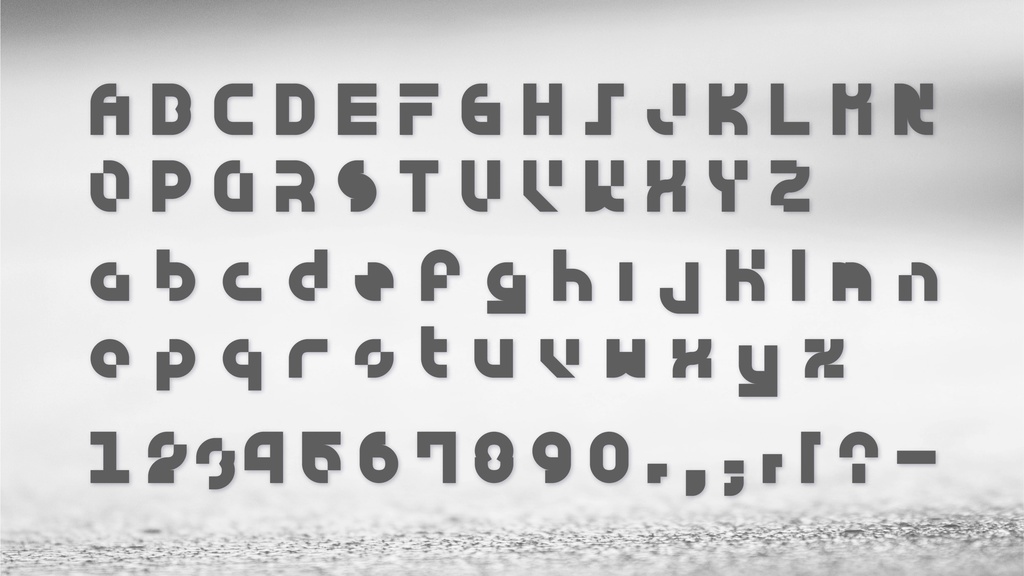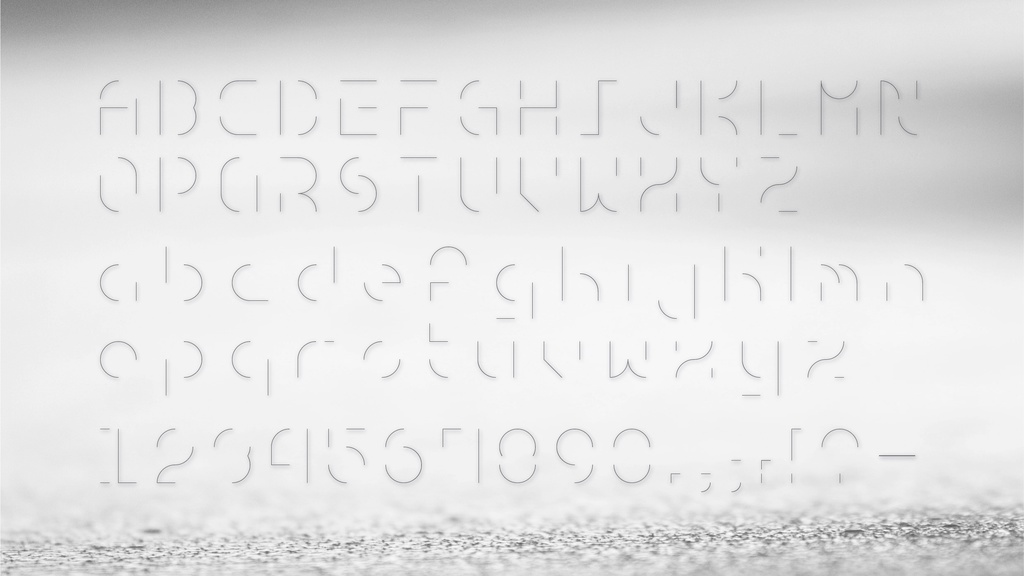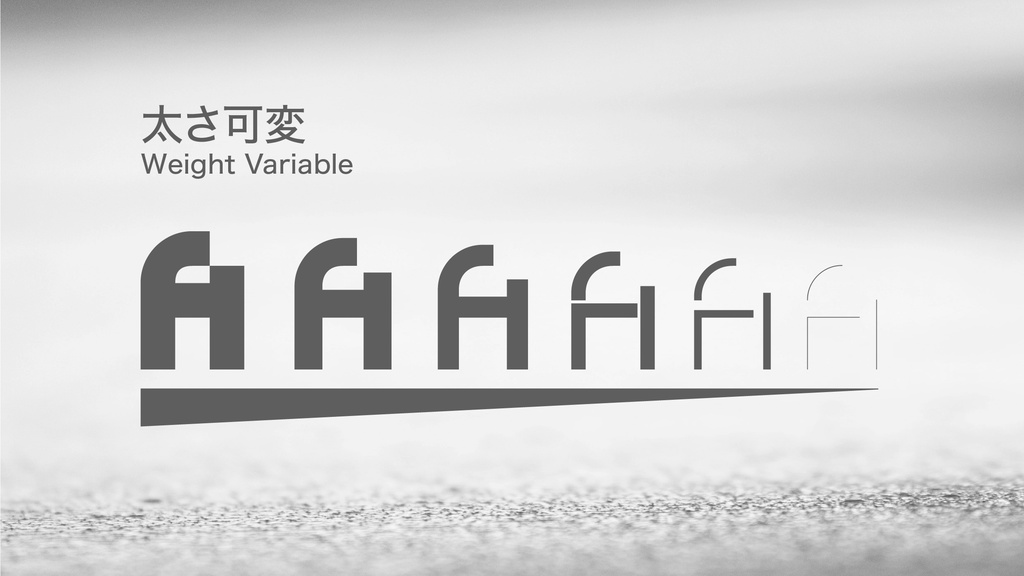
無料【フリーフォント】Amari Font 2/100 #100日フォントチャレンジ
Amari Font 2/100 📢📢📢特記事項📢📢📢 #100日フォントチャレンジ #100日チャレンジ 自分を挑戦した。 100日間て、1日1フォント作る。 デザインは不慣れなため、「すごく下手なデザイン」「他のフォントと似てる」「忙しくて制作できない」などが出てくることがあります。 もしそうなっても許してください!応援よろしくお願いします。 📢デザイン説明 一部画数省略フォントです。文明が衰退した後な機械化の感じ。 📢利用規約 このフォントは無料でダウンロードできる。 個人、商用どちらでも利用可能です。 もしもこのフォントが使用されたら、https://twitter.com/amari_designに教えていただけるとうれしいです! 本素材を使用した作品については、リツイートなどの形で宣伝させていただく場合があります。 フォントのインストール等の技術的なサポートはいたしません。使用して発生したと思われる如何なる問題についても、作者は責任を負わないものとします。 著作権を放棄することはありません。 商標を登録したり、作者であると主張したり、データ自体を販売または再販したりすることは禁じられています。 このコンテンツの最終的な解釈権は作者に帰属します。 内容補充とバージョン更新は製作続けるです。使用する際は最新バージョンにご注意ください。 📢収録內容 ラテン文字、数字だけてを含む70文字が含まれています。 ーーーーーーーーーーーー Twitter:https://twitter.com/amari_design Behance:https://www.behance.net/9f45706b ーーーーーーーーーーーー